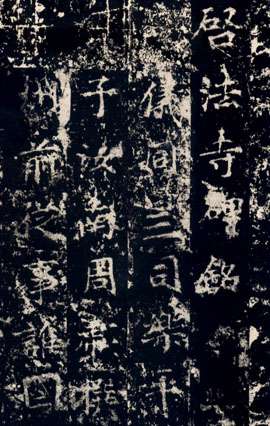
丁道护简介
谯县(今安徽亳县)人。生卒年不详。隋文帝时书家。官襄州祭酒从事。擅长真书,溢妍华致,在当时名声颇大,对初唐真书颇有影响。明丰坊《书诀》列记钟、王以来善书者,隋四人,丁道护名在其三。米芾《海岳名言》视丁道护与唐之欧阳询、虞世南侪类,并为变革古法者。北宋黄伯思《东观余论》称“道护不古不今,遒媚有法。”有刻本《启法兴国寺碑》,传世有剪裱拓本,为传世仅存唯一拓本孤本,已流日本。
启法寺,开皇四年(584)四月一日齐州刺史韦世康奉诏复建,初名“光福禅房”,后改“启法寺”,即宋之“龙兴寺”。隋民部员外侍郎福嗣兄弟为志,其父韦世康造寺事,于仁寿二年(602)十二月十五日立碑,周彪撰文,丁道护书丹,李宝刻字,赵励等人题名。此碑楷书,其书法工整典雅,笔法精熟,为丁道护的代表作。
宋蔡襄评《启法寺碑》语:“此书兼后魏遗法。……隋唐之交,善书者众,皆出一法,道护所得最多。”阮元《北碑南帖论》以为丁道护与房彦谦并出北派,有“方严遒劲,不类世南”之评。是碑正书,书法平正和美,与智永同一法嗣,当从“二王”而来,故蔡襄有“丁真永草”之称。
此碑原石已佚,传世宋拓本仅临川李宗瀚所藏钤有贾似道“魏国公印”。著录首见欧阳修《集古录跋尾》。启法寺碑于隋文帝仁寿二年立于湖北襄阳,是隋代诸碑中少数有书人署名的。丁道护这块碑是极成熟的楷书,间架平正,法度谨严,实为唐楷之先导,就算放在唐楷间也丝毫不逊色,可隐约见到唐代书家之笔法。